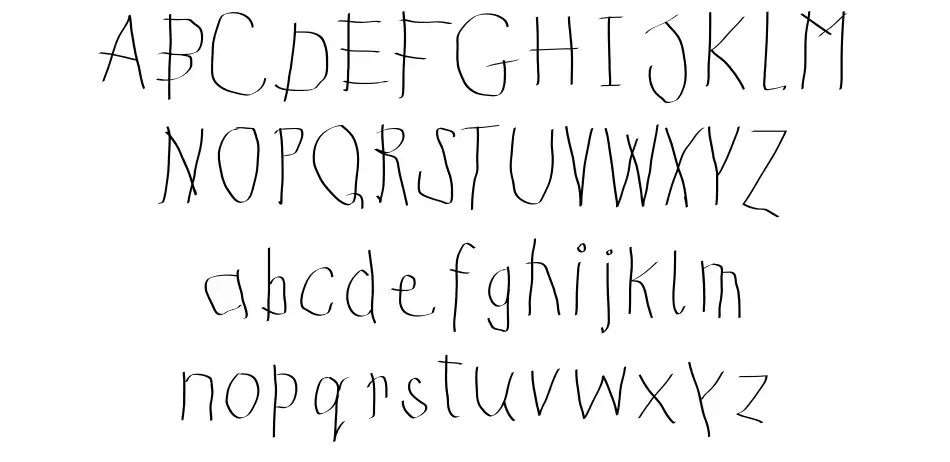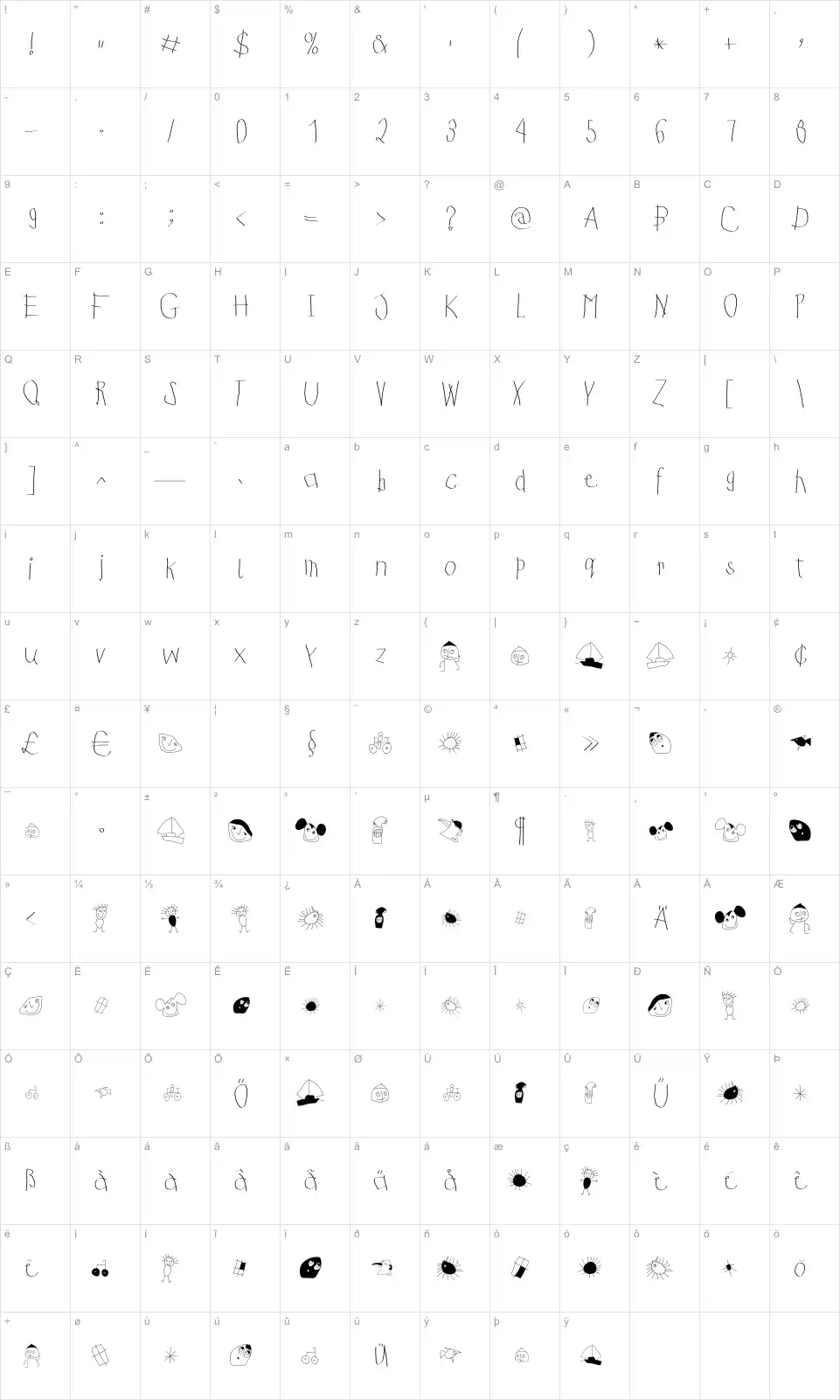
Descubra a Kids First Print Font, uma fonte script casual e divertida projetada pelo designer Manfred Klein. Se você está procurando por esta fonte livre, agora é o momento de descobrir como ela se encaixa em sua próxima arte. Com apenas alguns cliques, você pode baixar a fonte ou gerar um vislumbre de texto personalizado online para ter uma ideia antes de usá-la em suas criações. Essa fonte ficará perfeitamente em casa em qualquer projeto infantil ou trabalho que exija um visual retrô e delicado. Com uma categoria de script e uma forma handwritten, a Kids First Print Font é uma excelente escolha para quem deseja dar um toque especial a suas criações. Adicionada em 12 de julho de 2022, esta fonte já tem 4172 downloads e um tamanho de arquivos relativamente pequeno de 78 KB. Para mais informações, você pode visitar o site do designer, Manfred-Klein.ina-mar.com.
Designer: Manfred Klein